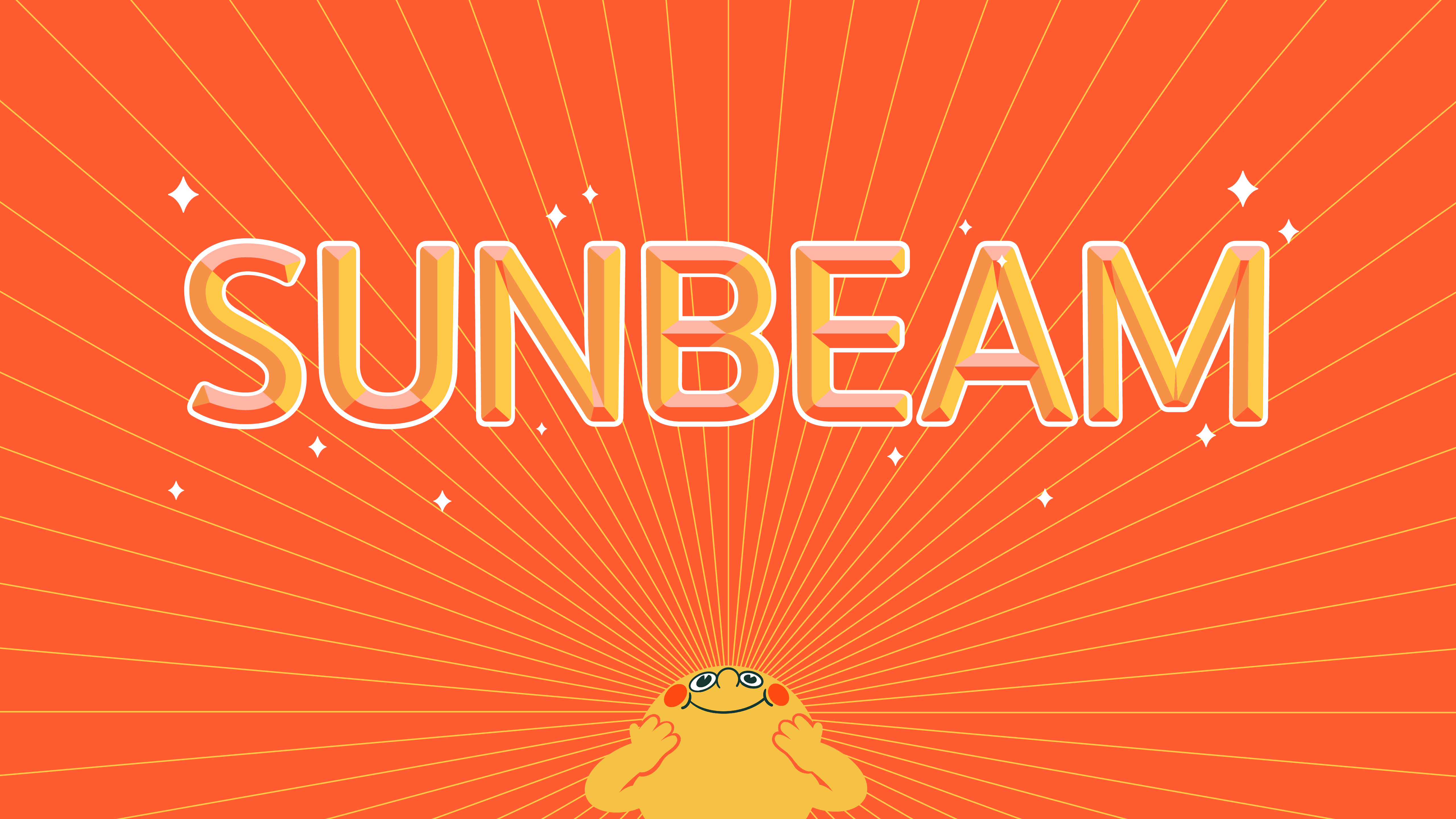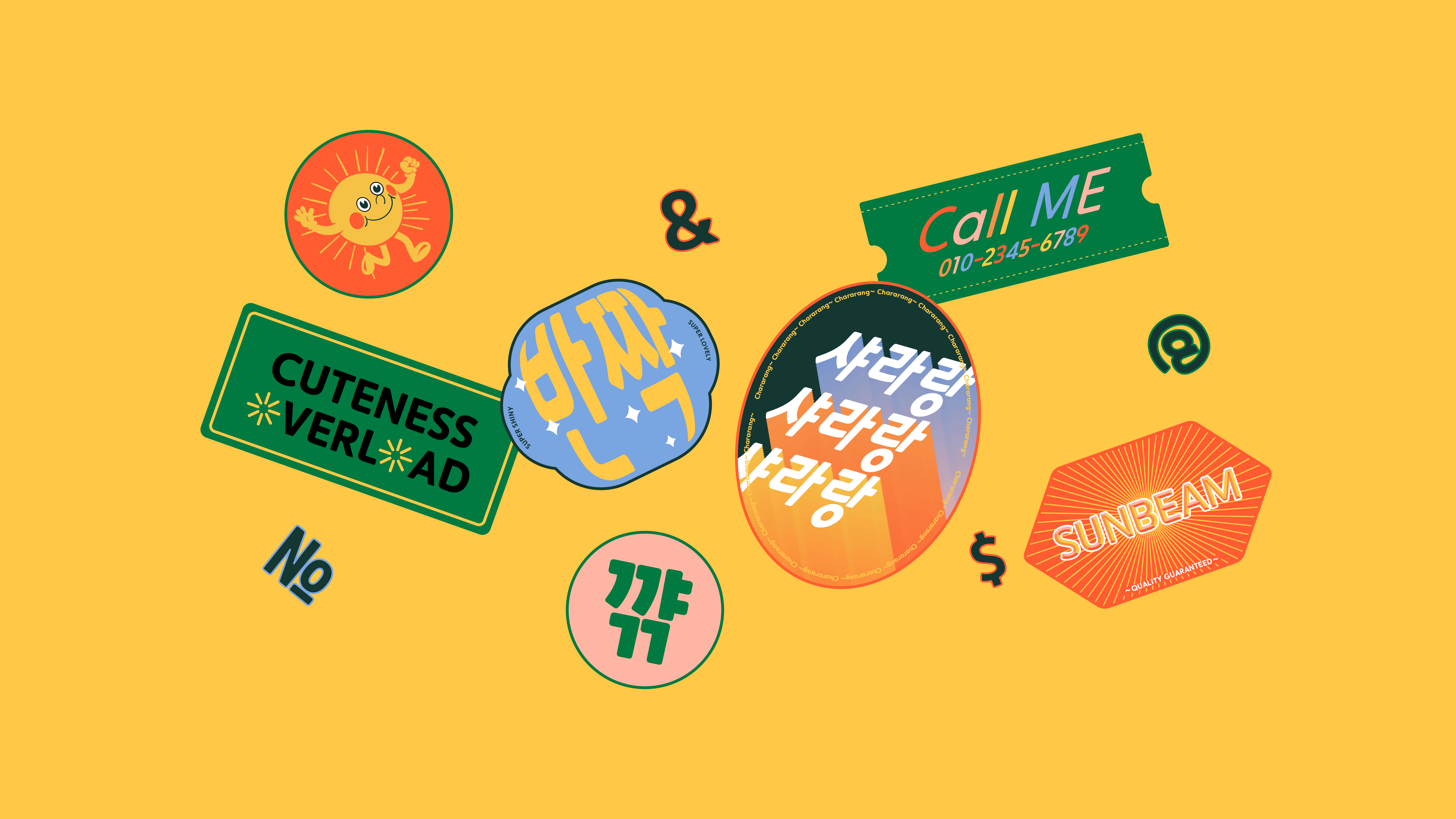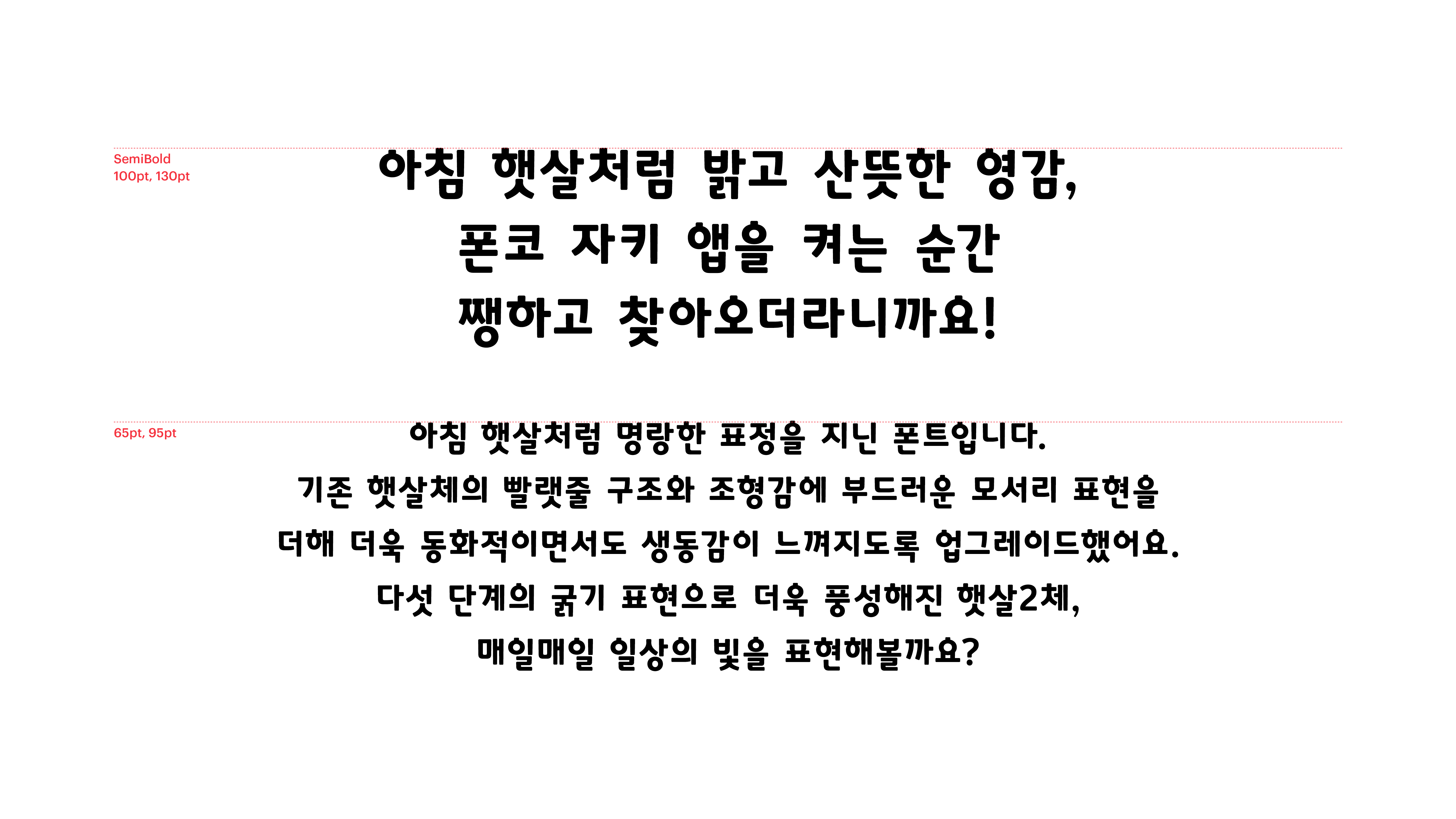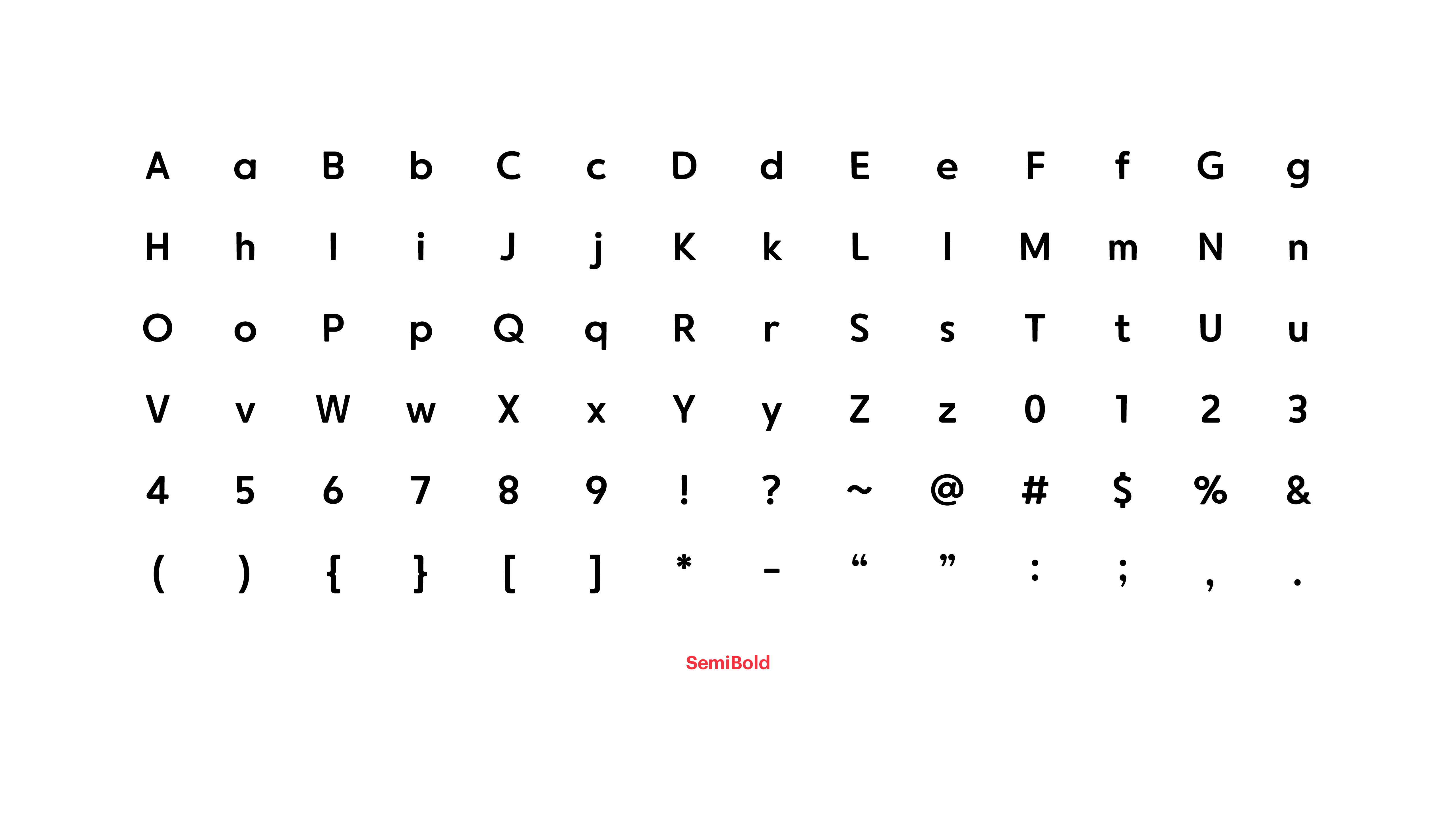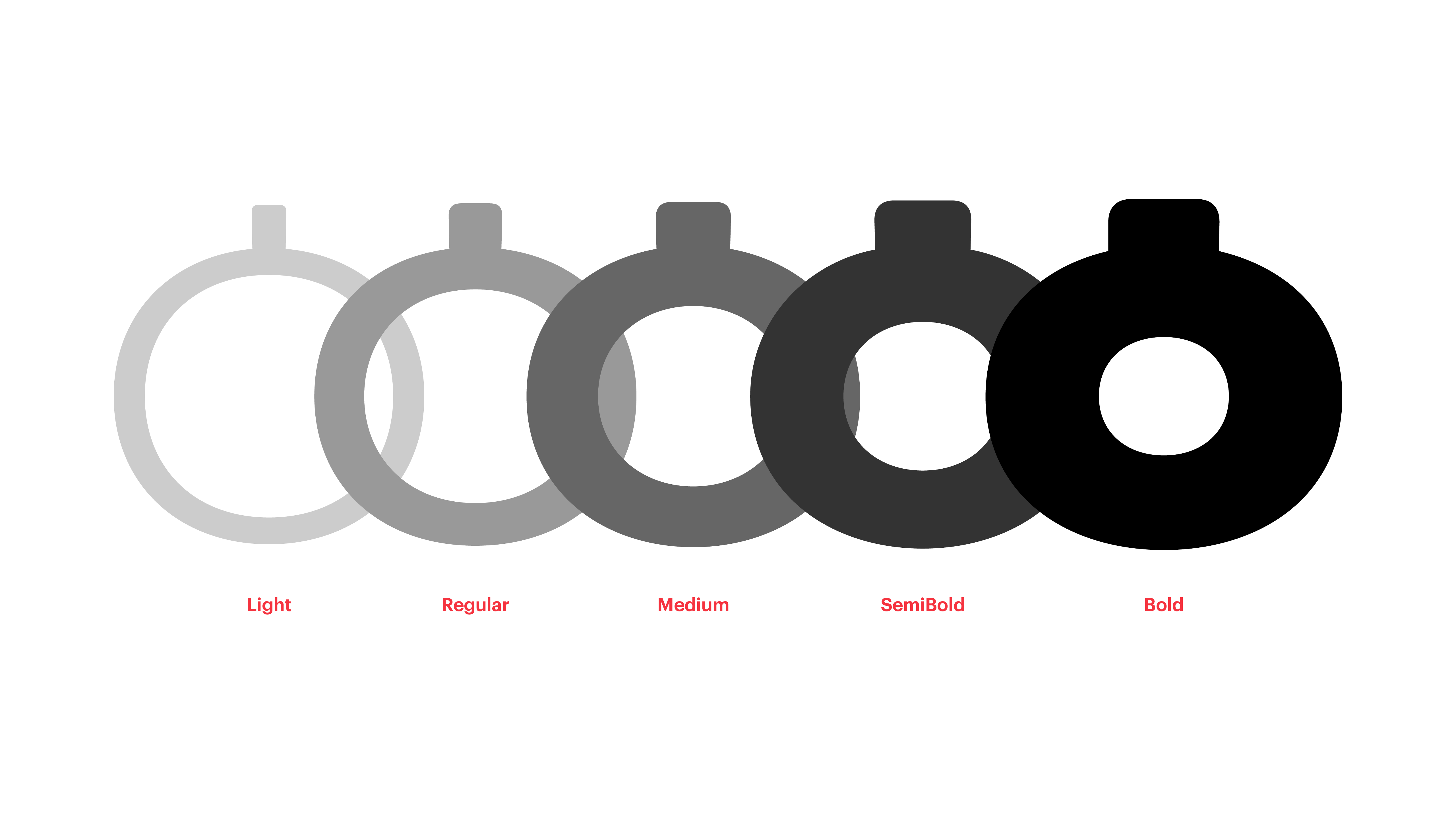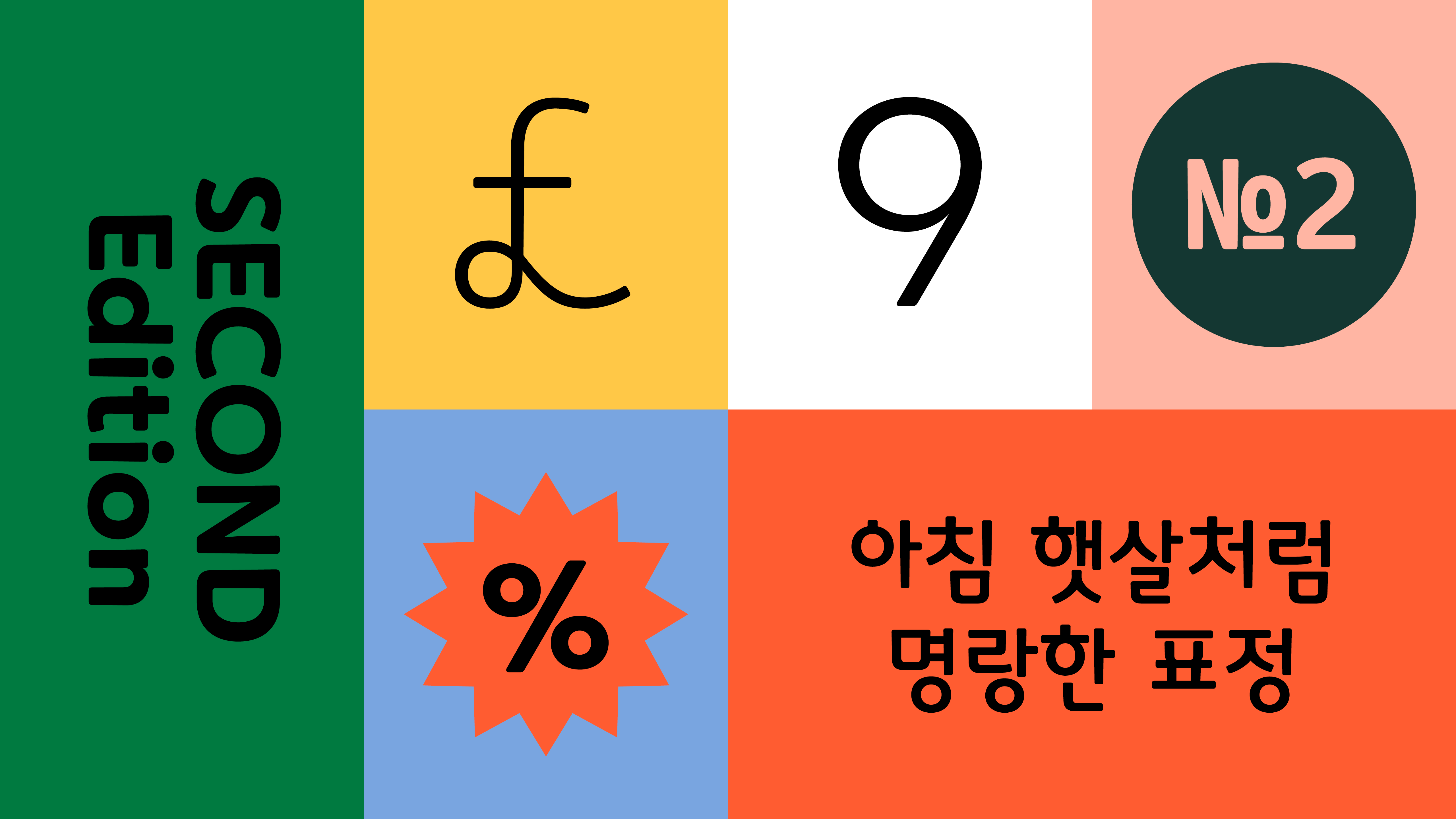
햇살2
Yoon 햇살2
아침 햇살처럼 명랑한 표정을 지닌 폰트입니다. 기존 햇살체의 빨랫줄 구조와 조형감에 부드러운 모서리 표현을 더해 더욱 동화적이면서도 생동감이 느껴지도록 업그레이드했어요. 다섯 단계의 굵기 표현으로 더욱 풍성해진 햇살2체, 매일매일 일상의 빛을 표현해 볼까요?